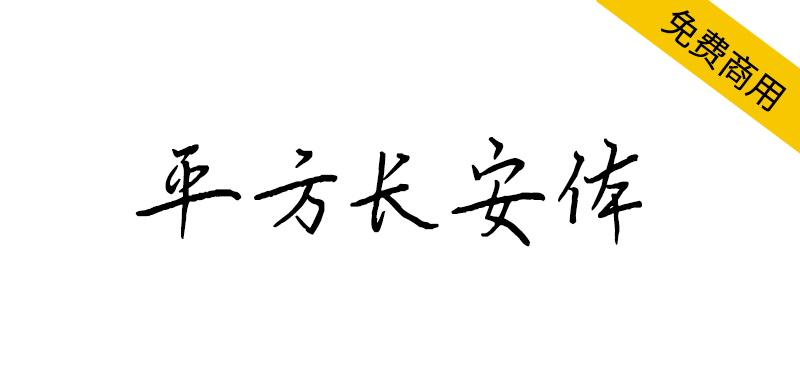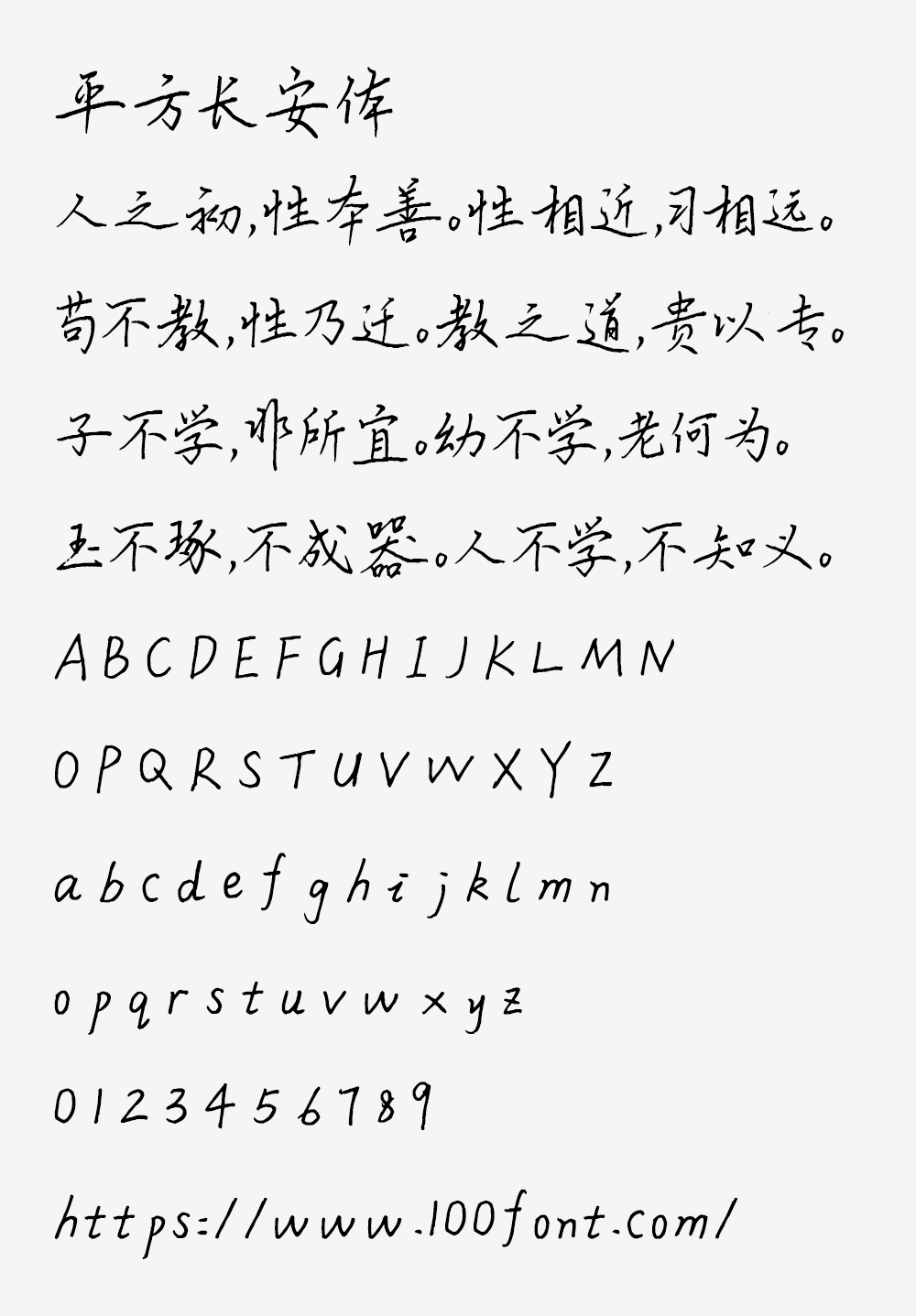
【平方长安体】一款笔画纤细而有力的硬笔手写字体
还在为设计作品缺乏个性而烦恼?这款笔画纤细却充满力量的硬笔手写字体,完美平衡了书法艺术与现代设计。中宫紧凑、连笔流畅的独特结构,让每个字都散发着优雅与张力。更惊喜的是,它完全免费商用!从广告创意到产品包装,立即解锁专业级设计的新可能。
【平方长安体】一款笔画纤细而有力的硬笔手写字体
平方长安体是一款兼具艺术性与实用性的硬笔手写字体,其设计特点鲜明,笔画纤细而不失力度,收放自如,中宫结构紧凑,连笔处婉转流畅。这款字体完美融合了书法韵味与现代设计需求,适用于广告创意、名片制作、产品包装及印刷设计等领域。